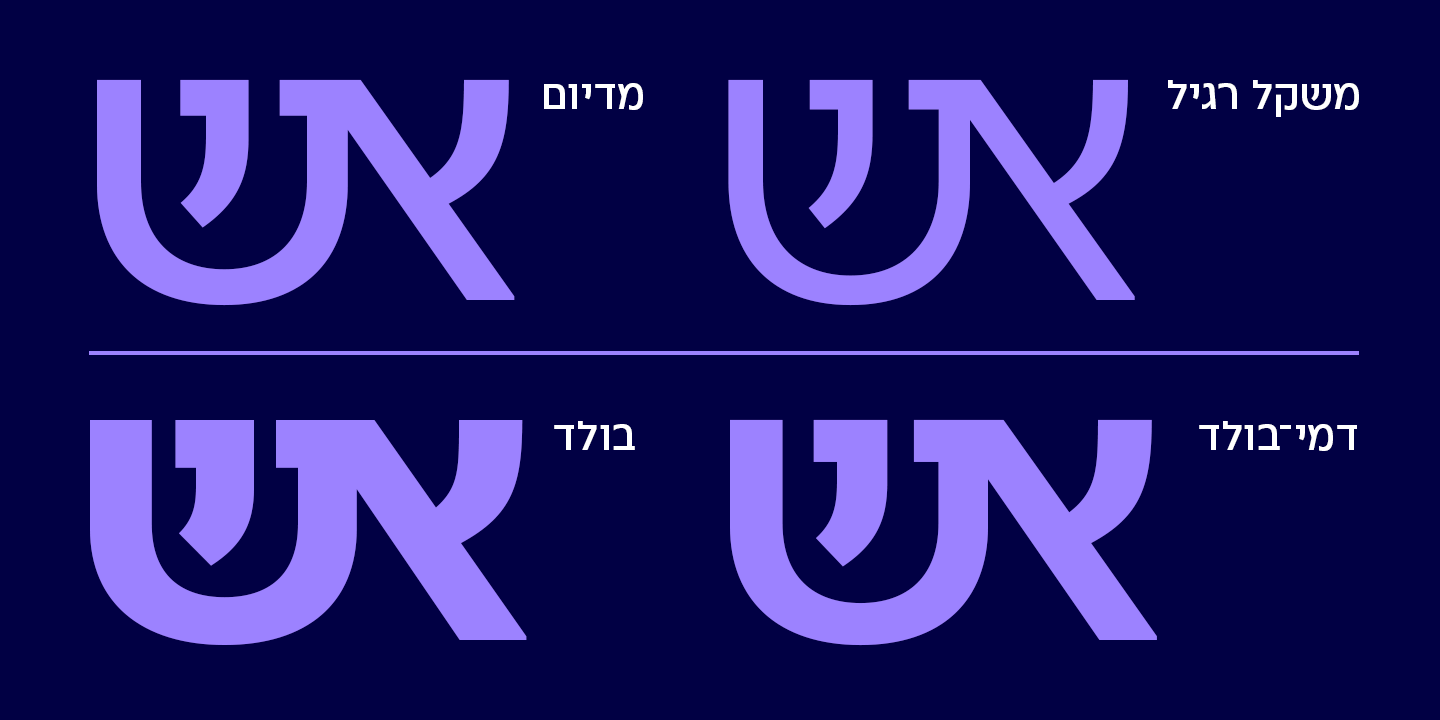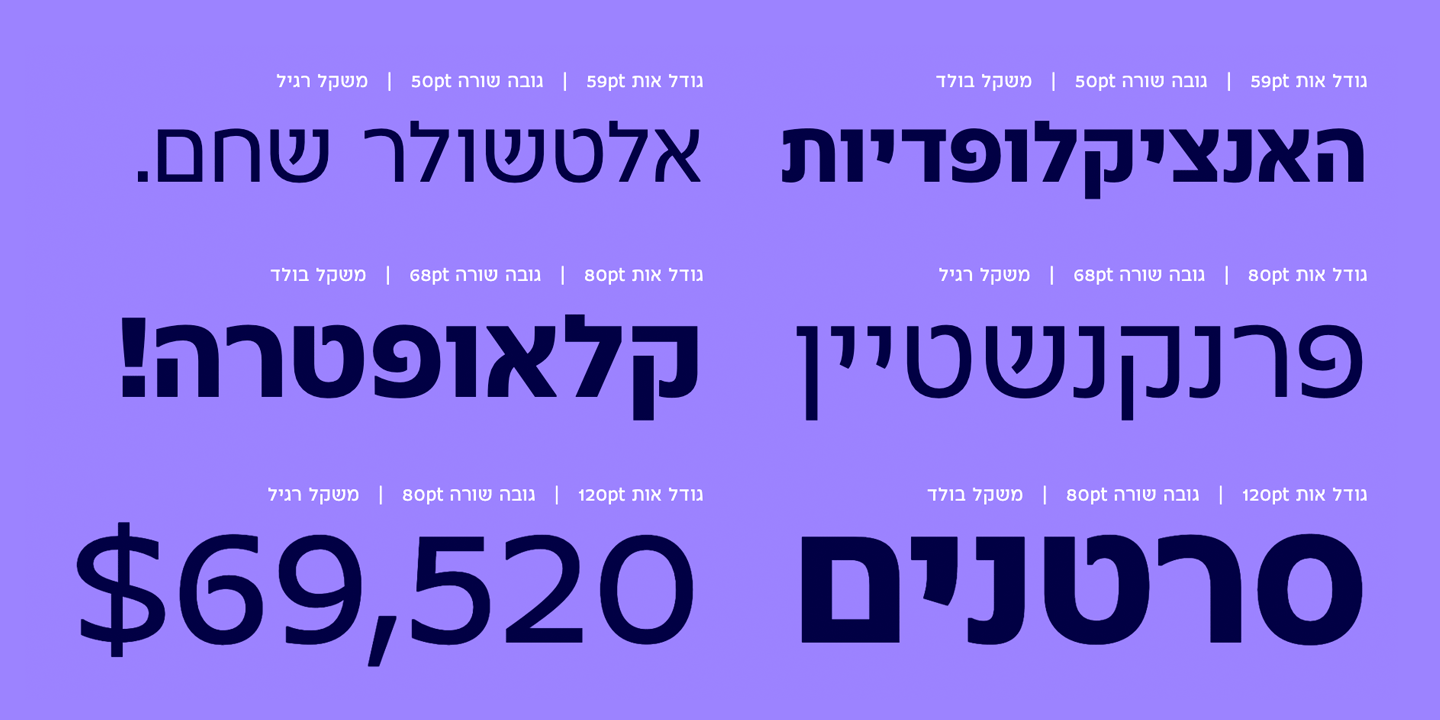
Teom Font Family
Une police de sens hébreu inspirée des lettres latines de la police Tahoma. « Twin » sert de substitut plus raffiné et harmonieux à l’hébreu par défaut de Tahoma, et également de police hébraïque indépendante et élégante pour les titres et les textes courts. En l’honneur de son lancement, Twin Font sert de police principale de notre site, à la place d’Afek.